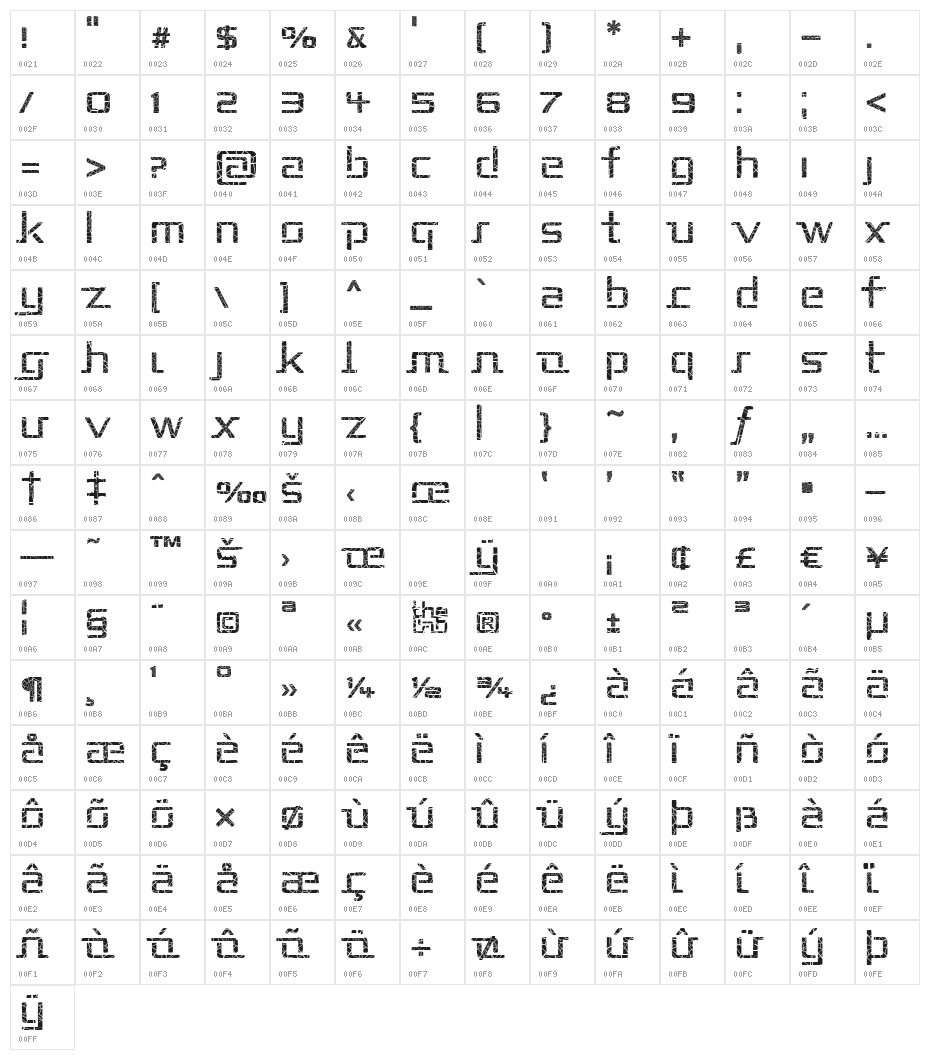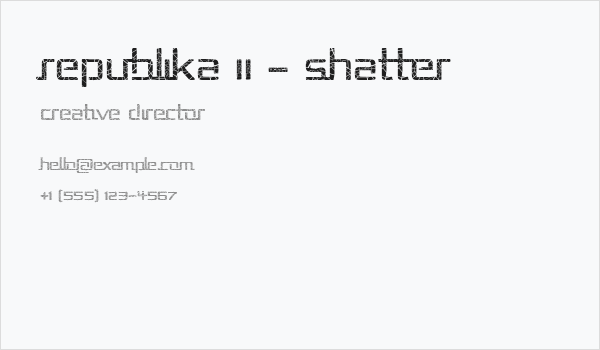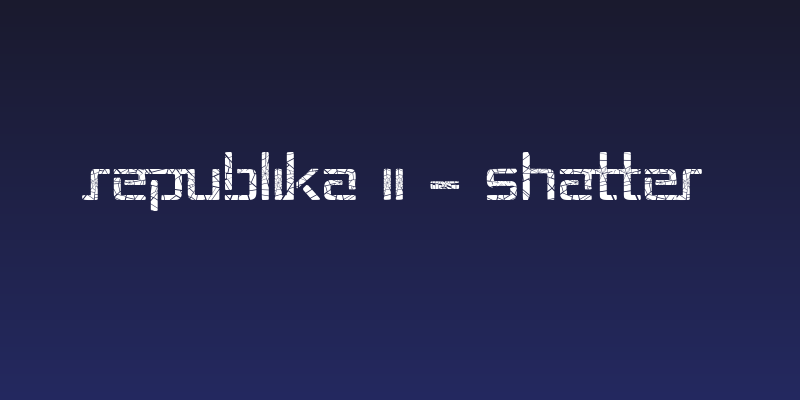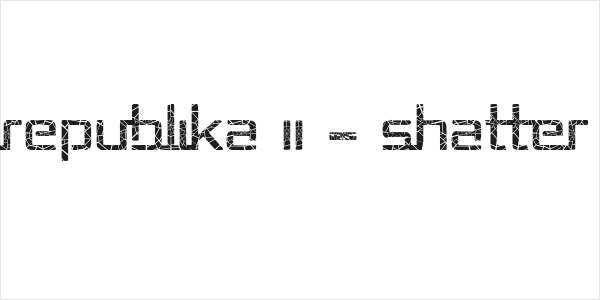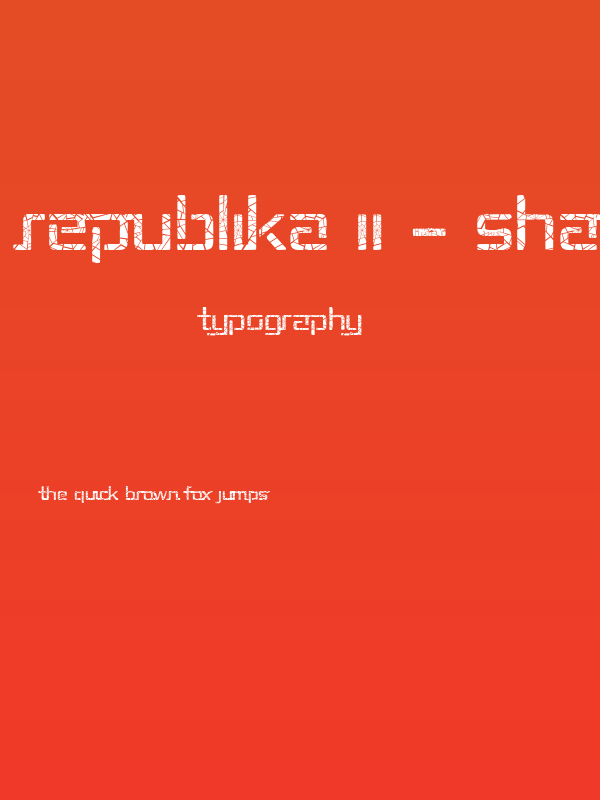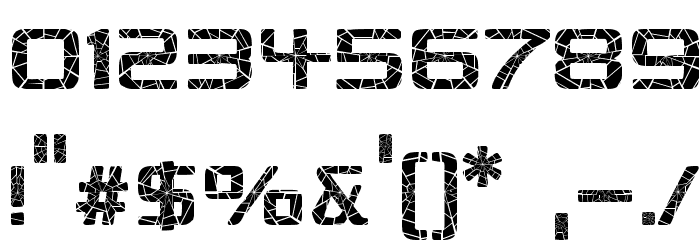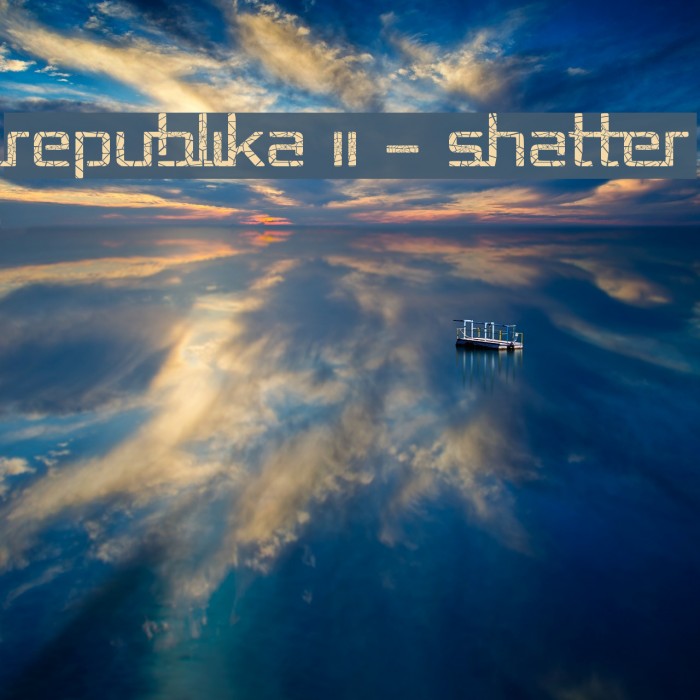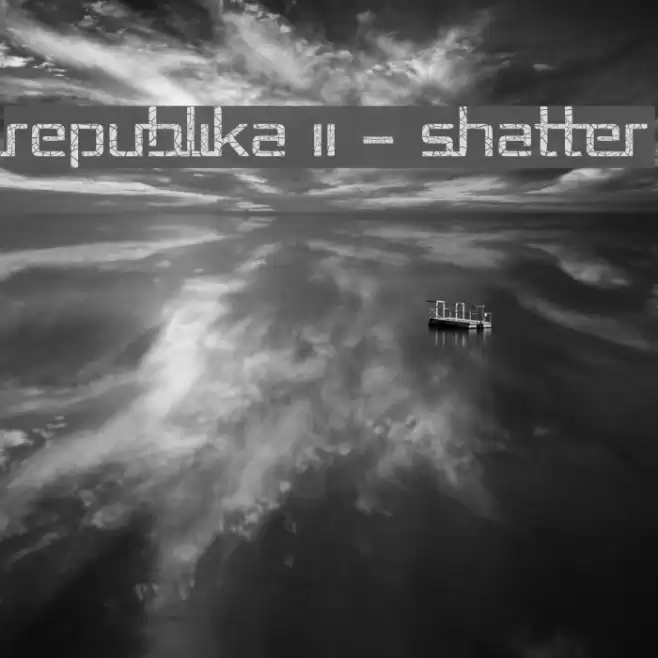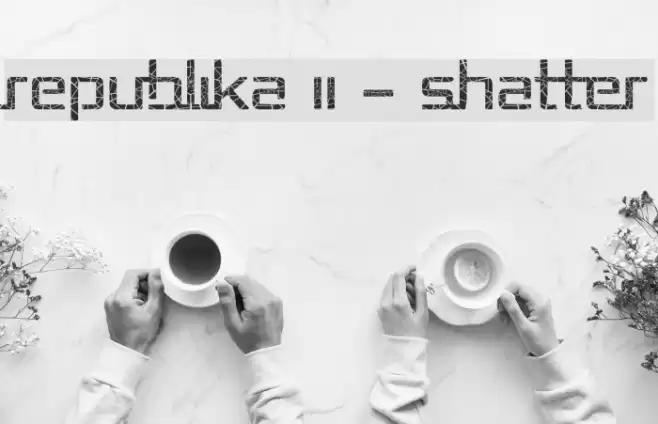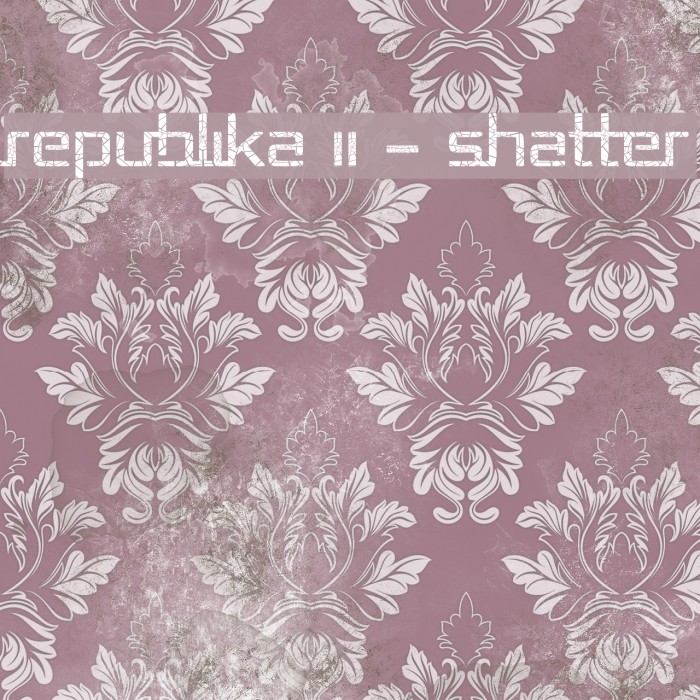
Republika II - Shatter Font
| Proyectos propuestos | Ideal for album covers, posters, video game graphics, and branding that requires a modern, edgy look. |